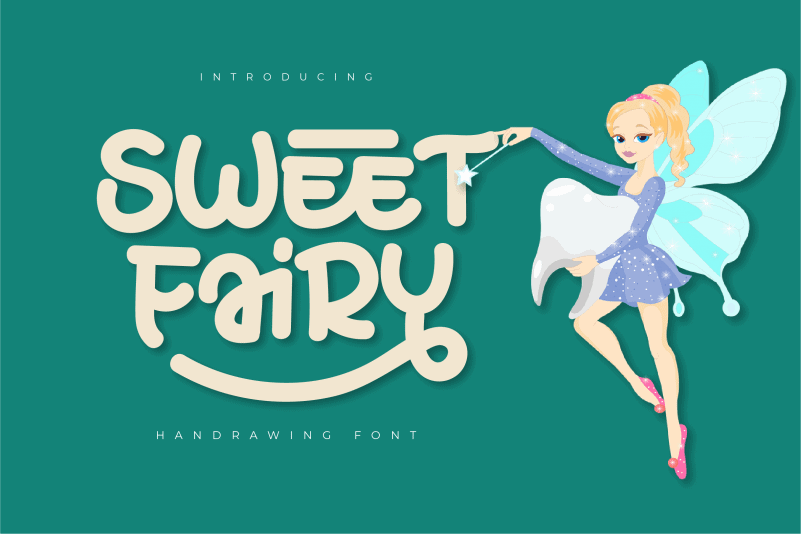
Sweet Fairy Display Font
A fonte Sweet Fairy Display Font é uma opção perfeita para quem busca expressar um estilo amigável e despojado no seu projeto visual. Escrevemos com a delicadeza de uma encantadora fada, mas também com o entusiasmo e vivacidade de alguém que toca sinfonias pela primeira vez. O design único desta fonte cria uma conexão natural com diversas ideias gráficas e tendências atuais. Ela é perfeita para aplicar em materiais de marketing, identidades corporativas ou até mesmo em designs de arte digital. A Sweet Fairy Display Font não tem limites; apenas sua imaginação! Seja você um criador visionário ou aquele que deseja dar uma repaginada ao estilo próprio já existente, esta fonte apresenta a oportunidade de explorar novas maneiras de expressão visual.